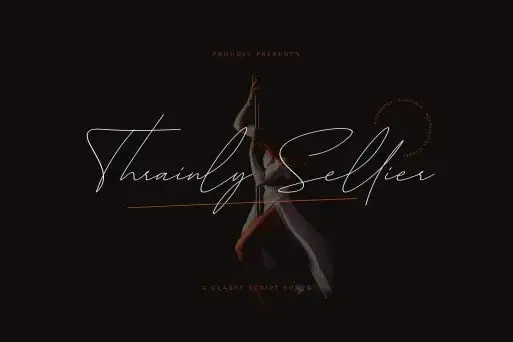
Thrainly Sellier Handwritten Font – Fonte Grátis
Thrainly Sellier Handwritten Font
Introduzimos a Thrainly Sellier Handwritten Font, uma fonte escrita à mão casual com um toque de elegância e relaxamento. Esta opção tipográfica é perfeita para quem busca uma identidade visual única, moderna e sofisticada. Feita pelo Namara Creative Studio, esta fonte script escrita à mão traz autenticidade em cada caractere, desde os gregos até os códigos de linguagem. A Thrainly Sellier Handwritten Font é versátil e pode ser usada em uma ampla variedade de aplicações, como cartões de postais ou postagens no Instagram. O único limite é a criatividade do designer que a usa. Com letras maiúsculas e minúsculas, números, sinais de pontuação, alternativas, ligaduras e suíças, ela é uma ótima opção para quem busca um visual autêntico em suas criações visuais.